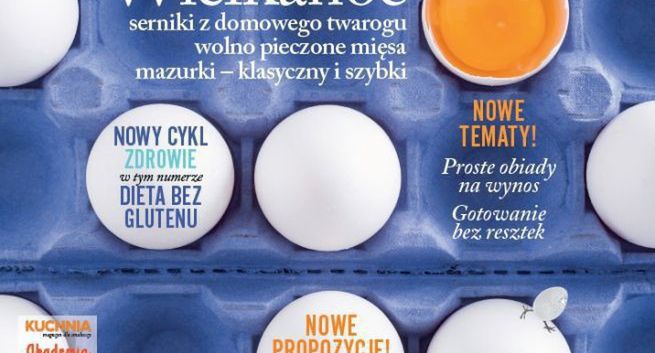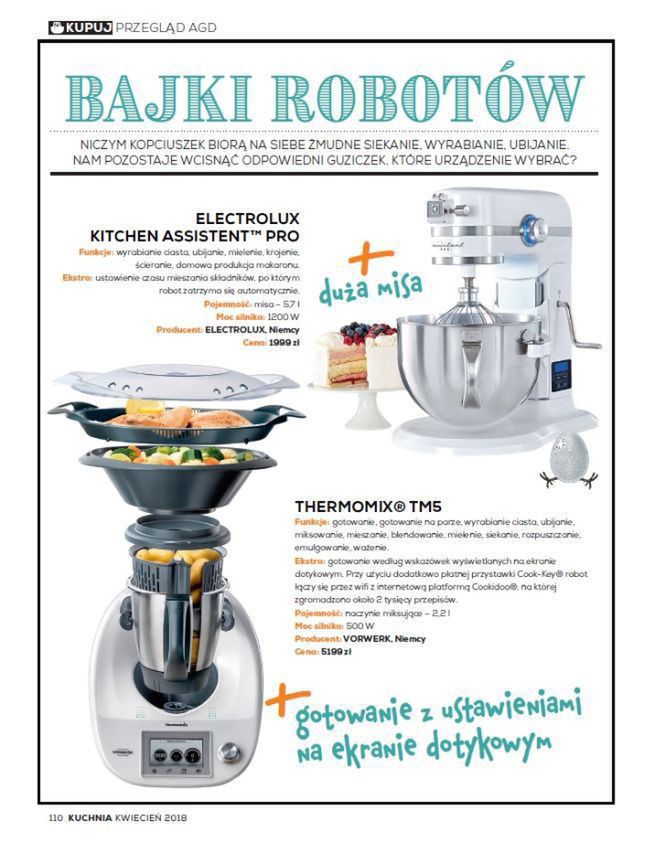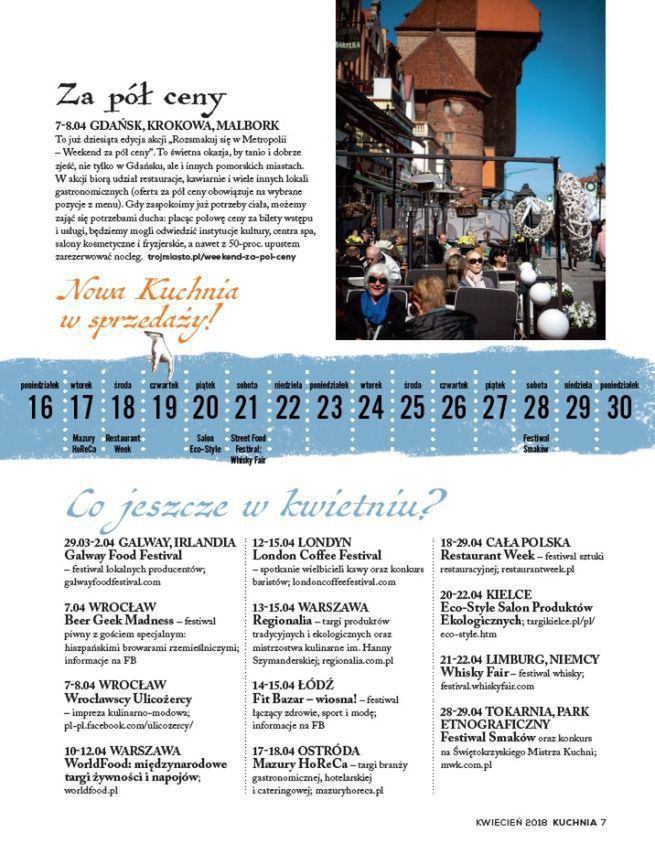
„Kuchnia” po relaunchu: nowe tematy, rubryki i autorzy, odświeżona czcionka i makieta
W czwartek ukazuje się kwietniowe, odmienione wydanie miesięcznika „Kuchnia. Magazyn dla smakoszy” (Agora). Pismo ma odświeżoną szatę graficzną, pojawią się także nowe rubryki i tematy. Magazyn ma promować m.in. niemarnowanie żywności.
Ewa Wagner, redaktor naczelna „Kuchni” mówi, że dbałość o niemarnowanie jedzenia jest dzisiaj jednym z ważniejszych trendów: zarówno kulinarnych, ale i społecznych. Dlatego redakcja postawi na ten temat duży nacisk.
- Nasi autorzy będą stale uzupełniać swoje przepisy o wskazówki dotyczące wykorzystywania resztek. Będziemy namawiali czytelników nie tylko do smacznego gotowania, ale i do robienia rozsądnych zakupów i znacznego ograniczenia wyrzucania żywności - dodaje Wagner.
W magazynie wprowadzone zostają tematy związane ze zdrowiem. - Rozszerzamy tematykę pisma o diety funkcjonalne, spełniające oczekiwania osób, które nie mogą lub nie chcą jeść konkretnych produktów. Zadbamy również o tych smakoszy, którzy nie mają czasu na długie gotowanie lub szukają pomysłów na przygotowanie pysznego i prostego obiadu do pracy lub do szkoły. Więcej uwagi poświęcimy gastronomii - co miesiąc polecimy kilka restauracji z różnych regionów Polski, które zostały sprawdzone przez naszych wysłanników. Do tego dział o podróżach kulinarnych rozszerzymy o propozycje z Polski - dodaje Ewa Wagner.
W „Kuchni” pojawią się nie tylko nowe tematy, lecz i rubryki. Nowością będzie dział poświęcony prostym posiłkom do pracy i do szkoły. Redakcja krytycznie odniesie się do diet, a także cyklicznie będzie proponować dania uwzględniające ograniczenia, jakimi podlega coraz większa liczba osób. W kwietniowym wydaniu będzie to dieta bez glutenu - na 18 stronach czytelnicy znajdą najważniejsze informacje i przepisy na dania bezglutenowe.
Nowością jest także ocenianie restauracji. Na łamach kolejnych wydań miesięcznika redakcja będzie polecać lokale w całym kraju, wyróżniające się stabilną jakością. W każdym numerze znajdzie się rozmowa z przedstawicielem branży na temat współczesnej gastronomii i trendów rynkowych. W kwietniowym wydaniu będą to: ukraińskie restauracje we Wrocławiu, kulinarna relacja z Lyonu oraz kuchnia Tomasza Olszewskiego z poznańskiej restauracji Concordia Taste. Nowością będzie też comiesięczny przegląd sprzętu gospodarstwa domowego - w najnowszym numerze będzie to przegląd robotów wielofunkcyjnych.
Odświeżeniu ulega wygląd pisma. - Zmieniamy szatę graficzną, aby lepiej zaprezentować nowe treści magazynu. Czcionka będzie bardziej pojemna i łatwiejsza do czytania. Wprowadzimy też nową typografię, żeby w piśmie - oprócz rzetelnych informacji - pojawił się element lekkości i zabawy. Zupełnie nowe winiety rubryk będą służyć lepszej nawigacji i orientacji w treściach. Do współpracy zaprosimy najlepszych fotografów i ilustratorów - opisuje Katarzyna Trzeszczkowska, kierownik artystyczna miesięcznika „Kuchnia”.
Na początku roku do grona współpracowników pisma dołączyli Tomasz Prange-Barczyński (z magazynu „Ferment” - w „Kuchni” pisze felietony o winie) oraz Marieta Marecka (autorka książek kulinarnych i programów w nc+, w „Kuchni” prowadzi rubrykę „Kuchnia na słodko”).